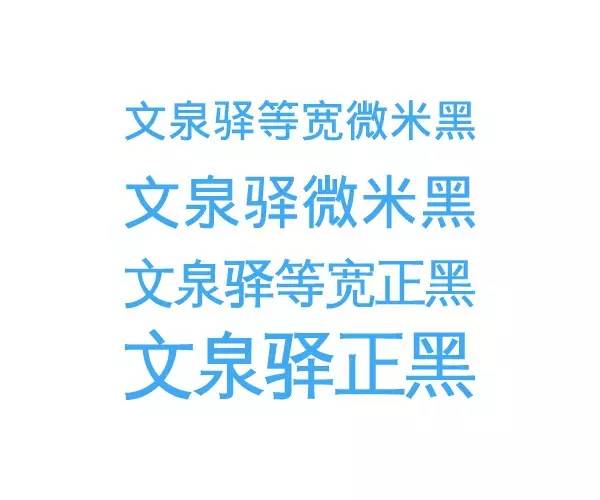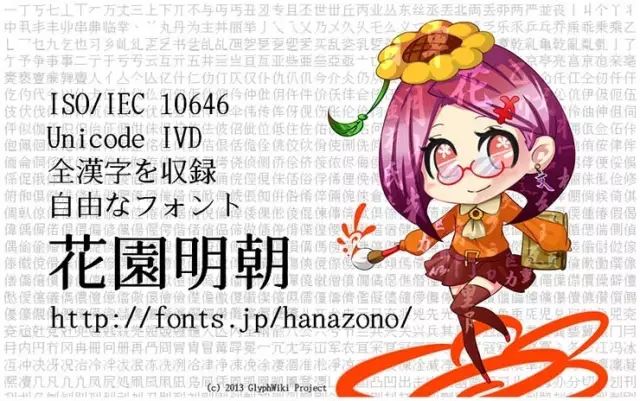
到底有哪些好看又免费的字体?这篇合集快收藏!
字体篇
到底有哪些免费商用的字体?
微软雅黑到底是不是免费的?
方正字库所有的字体都不能商用吗?
其实不止是新手
连老手也不是完全清楚
到底有哪些是可以免费商用的
所以今天
鸟哥笔记来帮大家梳理一下
哪些字体是可以免费商用的
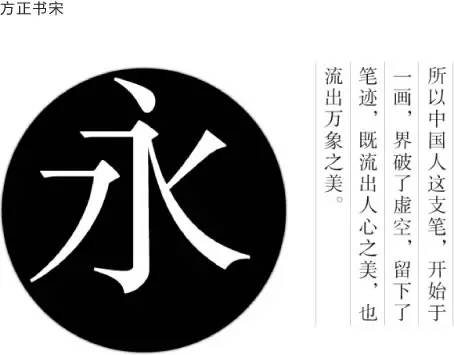
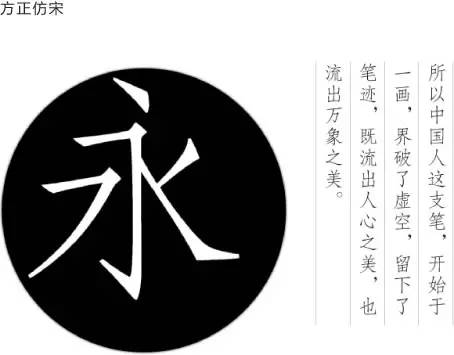
那么,到底有哪些好看又能商用的中文字体呢?
01 思源黑体
英文名称“Source Han Sans”,2014年7月16日首次发布,Adobe与Google领导开发的无衬线黑体,支持繁体中文、简体中文、日文及韩文,并且各有7种字体粗细。思源是涵盖字数最多的字体,且可以不受限制的免费使用,并且它还是一款好看的字体。
例如思源黑体:
02 濑户字体
濑户字体,是一款偏可爱风的字体,支持简体中文、繁体中文、日文,包含CJK常用汉字、平片假名、JIS第一至四级,共30000余字。
03 书体坊免费字体
专注于古今书法名家计算机字体开发的书体坊提供的免费字体。
04 站酷系列字体
“汉字百人舞”计划,由字体设计师胡晓波、刘兵克发起,在站酷网征集100位字体设计师共同完成一套字库创作,供所有人永久免费下载。
目前可供下载的包括站酷高端黑、站酷快乐体、站酷酷黑体、站酷意大利体(西文字体)。
05 文泉驿系列字体
由旅美学者房骞骞(FangQ)于2004年10月创建,集中力量解决GNU/Linux高质量中文字体匮乏的状况。目前已发布第一个完整覆盖GB18030汉字(包含27000多个汉字)的多规格点阵汉字字库,第一个覆盖GBK字符集的开源矢量字库(文泉驿正黑),并提供了目前包含字符数目最多的开源字体——GNU Unifont——中绝大多数中日韩文相关的符号。这些字库已经逐渐成为主流Linux/Unix发行版中文桌面的首选中文字体。
目前有:
清晰锐利的传统中文界面:文泉驿点阵宋体
柔和圆润的现代中文界面:文泉驿正黑
柔和与清晰的智能组合:文泉驿点阵正黑
兼顾中英文对齐的等宽开源字体:文泉驿等宽正黑
很小很强大的高质量矢量字体:文泉驿微米黑
经典的等宽点阵中文字体:文泉驿Unibit
06 王汉宗字体
由研发天蚕字库的台湾中原大学数学系王汉宗教授先分别在2000年和2004年先后捐赠出十套WCL系列字型和32套新字型,全部採用GPL授權,供大家免費使用。老师的为人值得敬佩!
07 花园明朝体
花园明朝 (Hanazono) 是一款免费字体,为 GlyphWiki 所开发,字形数量共 45090 + 47186 个,几乎收录了所有汉字字形。缺点是字形以日本字形为准,有一些字不符合中文书写规范(不论是大陆规范还是港台规范)。
08 濑户字体
濑户字体,是一款偏可爱风的字体,支持简体中文、繁体中文、日文,包含CJK常用汉字、平片假名、JIS第一至四级,共30000余字。
09 庞门正道标题体
这个字体是由庞门正道以及字游空间创意工作室联合制作的。
10 台湾教育部系列字体
台湾教育部推出的Big5台湾标准字体。
台湾教育部标准楷书
台湾教育部标准宋体
台湾教育部国字隶书
其他
台湾明体(类似康熙字典体)
刻石錄:刻石錄鋼筆鶴體、刻石錄明體、刻石錄顏體
全字库:全字库说文解字、全字库正宋体、全字库正楷体
手写杂字体(851手写杂字体,自由改造与再配布,可商用,但保留著作权)
Fandol字体(一家字体公司破产了,所以变成开源了)
那么,还有哪些英文字体是免费的呢?鸟哥笔记也整理了一些。
01 Google Fonts
谷歌字体是你在搜索免费字体时搜索结果最先返回的结果之一。这个庞大的“字体库”有超过800个不同类型的字体集,从sans serif到手写字体,单间距字体等等。
web的字体渲染器广泛使用谷歌字体,以获得更快、可靠的字体托管。然而,大多数设计师不知道的是,谷歌字体中的字体是可下载的。并且,所有的谷歌字体都是开源的,你可以随意使用它们。
02 Font Squirrel
Font Squirrel是另一个可靠的可以下载高质量免费字体的网站。Font Squirrel的大部分字体也有商业许可证。为了避免出现复杂情况,在下载之前,用户可以更容易地检查每个字体的许可证。
Font Squirrel还提供了一系列有用的工具,包括创建你自己的网络字体和字体标识符的Webfont,它可以帮助你根据图像检测和查找字体。
03 FontSpace
这个网站拥有超过32000个免费字体,网站的常驻设计师超过2100名,同时它也是74.6万名喜欢字体的会员的“家”。
你可以使用FontSpace来查找大量的免费字体,以供你的个人项目使用。仅仅在浏览的时候通过在对应的字体上悬停鼠标,就可以在下载之前找到字体的许可。
如果你是一名注册会员,你甚至可以创建一个个人收藏来更方便地访问字体。
04 DaFont
DaFont是另一个可以下载免费字体的流行平台,该网站的大部分字体只支持个人使用,但也有大量拥有商业许可证的字体。
DaFont突出的一个特点就是它的分类系统。它允许你根据不同的主题查找并浏览它的字体集,比如恐怖主题字体、视频游戏字体、情人节主题字体等等。这为设计师提供了一种更简单的查找方法,可以快速为不同类型的项目找到字体。
05 Abstract Fonts
Abstract Fonts是一种包含了一系列高质量字体的网站。它在用途上并没有限制,也就是说在个人和商业项目中都是许可的,可以免费使用。但是为了以防万一,还是要记得在下载之前检查一下许可证。
该网站还提供了一个有趣的分类系统,便于浏览,你可以很容易地使用这些可视化的类别找到不同主题的字体。
06 Behance
Behance并不是一个针对于字体的平台。它更像一个关于设计的社交网络,设计师们可以通过这个平台分享他们创造的最好的作品。
设计师在Behance网站上分享了很多免费的内容,包括免费的字体。在平台上通过快速搜索将会返回无穷无尽的字体结果列表,可供免费下载。
在Behance找字体的最具优势的一点是,你在这个平台上找到的字体通常都有独特的设计,比你在其他网站上找到的字体更具有独特性。
07 FontStruct
FontStruct实际上是一种字体构建工具,它允许你通过几何图形来创建你自己的字体。该工具同时可以使用你的设计生成TrueType字体,可以应用于任何网站设计和任何你想要使用的工作中。
该网站还包括一个包含43000个字体的文件包,大多数都是由和你一样的人创造的,所有你可以免费下载。你甚至可以克隆其他用户创建的字体来设计你自己独特的字体。
08 1001 Fonts
别让这个名字骗了你,1001 Fonts包括超过9000种字体,该网站提供了一个经常更新的高质量字体集合,许多字体可供商业使用。
你还可以根据字体样式、大小、甚至字体权重来针对性的查找1001 Fonts中的字体,以快速找到与你的设计项目相匹配的字体。
09 Urban Fonts
Urban Fonts是另一个寻找免费字体的好地方。该网站为每一种字体提供了一个更详细的页面,显示了字体的所有字符以及在下载之前可以测试字体效果的工具。
你也可以根据不同的主题浏览字体,并创建一个帐户来保存字体。
10 FontSpring
FontSpring是一个更高级的字体市场,充满了优质的字体家族。但是,这个网站只允许你从这些字体家庭中下载一些免费的字体,以供你使用。你可以在每个字体页面中找到关于字体许可证的详细信息。